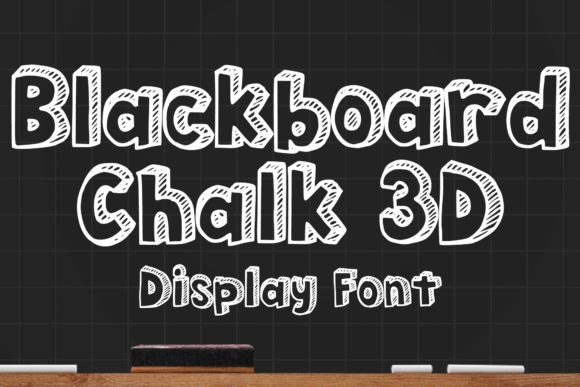
Blackboard Chalk 3d
Blackboard Chalk 3D – A Fonte que Transforma Ideias em Arte Casual
Se você busca uma tipografia que una a espontaneidade da caligrafia feita à mão com a textura inconfundível do giz, Blackboard Chalk 3D é a escolha certa. Essa fonte traz um toque lúdico e ao mesmo tempo profissional, ideal para projetos que precisam se destacar sem perder a leveza.
- Estilo desenhado à mão: linhas irregulares que simulam o traço de um giz sobre quadro negro.
- Textura em 3D: profundidade sutil que dá vida ao texto, perfeito para chamar a atenção.
- Versatilidade: funciona em camisetas, capas de livros, cardápios de restaurantes, posts de blog, cartões comemorativos e stickers.
- Leitura fácil: apesar do aspecto “rasgado”, a fonte mantém boa legibilidade em diversos tamanhos.
Aplicações Ideais
Blackboard Chalk 3D brilha em ambientes criativos onde o look descontraído é essencial:
- Camisetas e vestuário: designs que chamam o olhar nas ruas e nas redes sociais.
- Capas de livros e e‑books: capas que transmitem personalidade e convidam à leitura.
- Cardápios de restaurantes: menus que despertam o apetite e reforçam a identidade do estabelecimento.
- Blogs e artigos online: títulos que aumentam a taxa de cliques e melhoram o SEO.
- Cartões de felicitações: mensagens que tocam o coração com um toque artesanal.
- Stickers e adesivos: peças colecionáveis que se destacam em laptops, cadernos e paredes.
Por que escolher Blackboard Chalk 3D?
Além da estética única, a fonte é otimizada para SEO: usar Blackboard Chalk 3D em headings (H1‑H3) e textos alternativos ajuda os mecanismos de busca a reconhecer a relevância visual do seu conteúdo. Combine-a com palavras‑chave como “fonte estilo giz”, “tipografia criativa” e “design informal” para melhorar ainda mais seu ranqueamento.
Blackboard Chalk 3D oferece o equilíbrio perfeito entre criatividade e praticidade. Seja para um projeto comercial ou pessoal, ela garante que sua mensagem seja vista, lembrada e, acima de tudo, sentida. Experimente hoje mesmo e dê vida às suas criações com o charme irresistível de um giz em 3D!